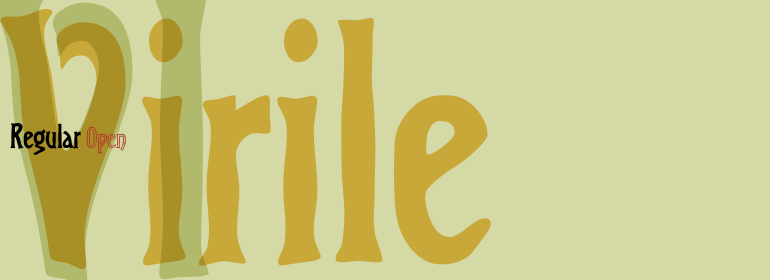
Virile
Virile,这款字体结构工整、笔画清晰,兼顾美观与易读性,适用于标题、正文、海报、包装、LOGO 等多种场景。字形优雅稳定,风格百搭耐看,适配日常排版与创意设计,让文字呈现更舒适、更具质感。Virile一笔一画,皆是细节,以均衡的比例、流畅的线条打造舒适视觉体验,字形端正大气,风格简约现代。无论是商业设计、品牌宣传还是日常排版,都能轻松驾驭,让文字更有格调与力量。Virile字体下载。
The Virile and Virile Open fonts are late nineteenth-century typefaces in a rustic style. Use the Virile fonts to add charm to book covers and posters relating to natural history and decorative arts.